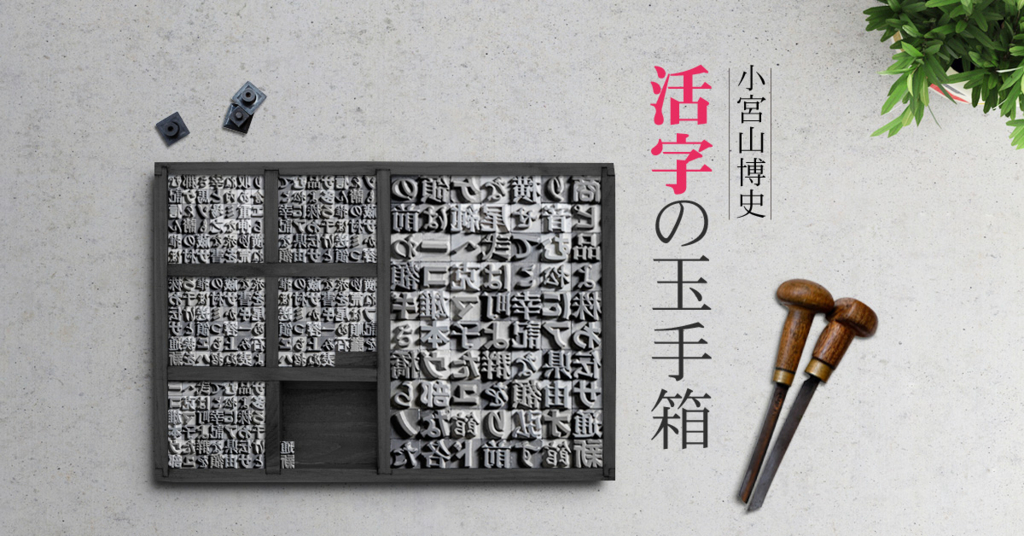
小宮山博史「活字の玉手箱」
ダイナコムウェア公式サイトのダイナフォントストーリーで2017年7月20日(木)より書体史研究者であり書体デザインの第一人者である佐藤タイポグラフィ研究所代表・小宮山博史氏によるコラム・小宮山博史「活字の玉手箱」の連載が開始された。
第一回では活字の歴史が誕生から語られている。
小宮山博史
Profile●国学院大学文学部卒業後、佐藤タイポグラフィ研究所に入所。佐藤敬之輔の助手として書体史、書体デザインの基礎を学ぶ。佐藤没後、同研究所を引き継ぎ書体デザイン・活字書体史研究・レタリングデザイン教育を三つの柱として活躍。書体設計ではリョービ印刷機販売の写植書体、文字フォント開発・普及センターの平成明朝体、中華民国国立自然科学博物館中国科学庁の表示用特太平体明朝体、大日本スクリーン製造の「日本の活字書体名作精選」、韓国のサムスン電子フォントプロジェクトなどがある。武蔵野美術大学、桑沢デザイン研究所で教鞭をとり、現在は阿佐ヶ谷美術専門学校の非常勤講師。印刷史研究会会員。佐藤タイポグラフィ研究所代表。著書に《本と活字の歴史事典》、《明朝体活字字形一覧》、《日本語活字ものがたり─草創期の人と書体》などがある。